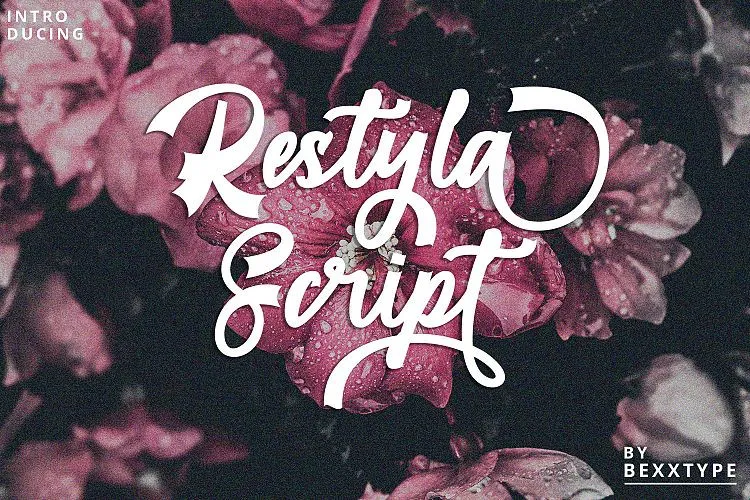
A Restyla Script é uma elegante fonte de escrituração que destaca-se pela sua base de linha variável, linhas suaves e toques clássicos e elegantes. Introduzimos a Restyla Font – um novo script fresco e moderno com estilo de escrita à mão, caracteres decorativos e uma base de linha dançante! Ela brilha especialmente em invitações, cartas de cumprimentos, materiais de marcação, cartões de negócios, citações, posteres e muito mais. Com 496 guílas incluídas, a Restyla Script oferece alternativas de caracteres divididos em várias funcionalidades do Open Type, como Swash, Conjuntos Estilísticos, Alternativas Estilísticas e Alternativas Contextuais. Descubra por si mesmo a beleza da Restyla Script na sua próxima peça gráfica!